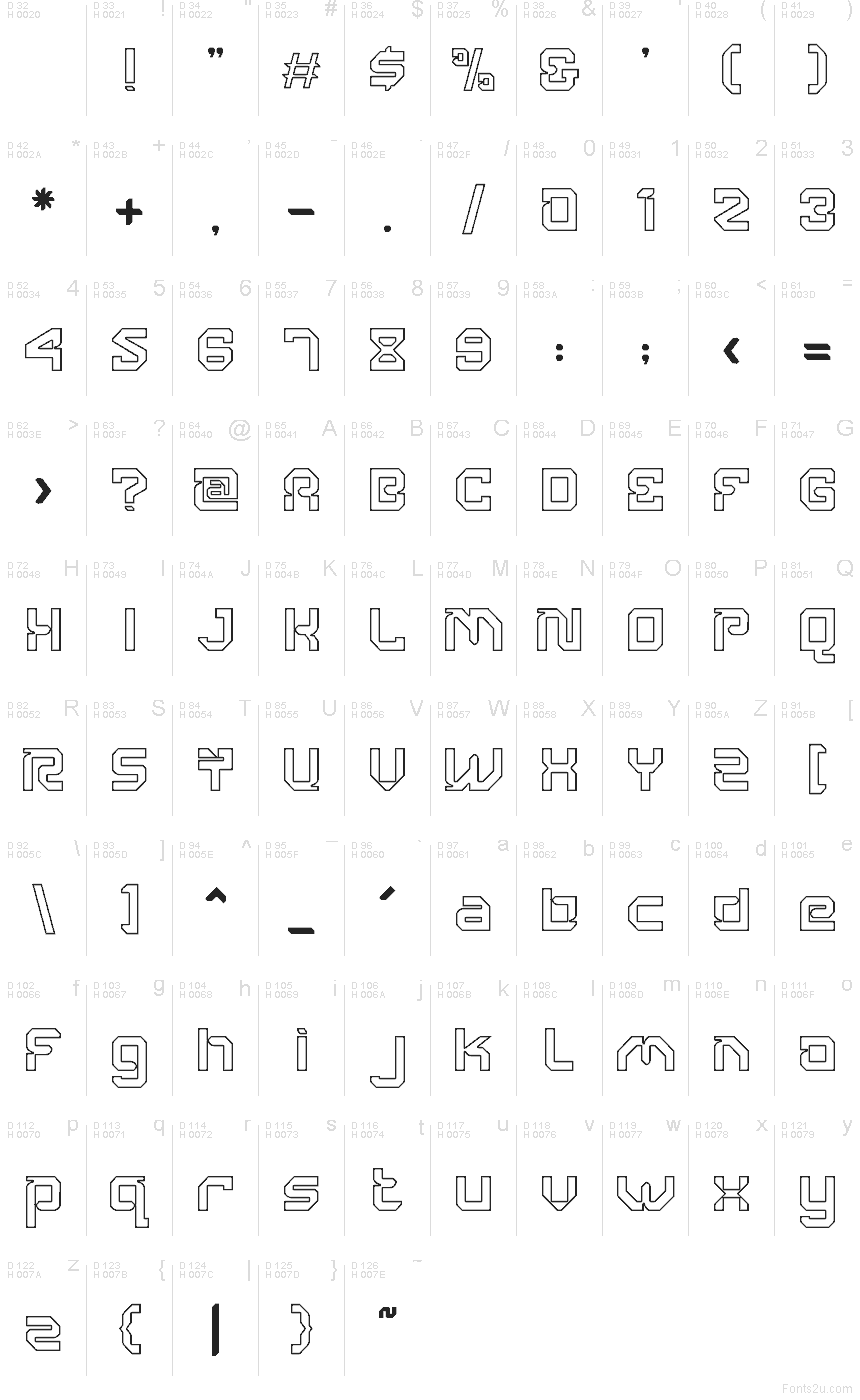
Cyber Crown Four od Putracetol Studio je bezplatné futuristické písmo typu outline, definované protáhlými čtvercovými liniemi a seříznutými rohy, které písmenům dodávají rytmus připomínající obvody. Konstrukce s dvojitou linkou udržuje tvary otevřené a lehké, takže design působí spíše jako obrysové panely nebo neonové trubice než jako masivní technický blok.
Tato struktura dává smysl u herních titulů, plakátů sci-fi, e-sportovního brandingu, hudebních letáků a nadpisů rozhraní, kde výrazná silueta odvádí hlavní vizuální práci. Otevřený obrys také poskytuje prostor pro vrstvení, což jej činí obzvláště užitečným pro koncepty log, úvodní obrazovky a grafiku na merchandising, které vyžadují ostrý digitální rám, aniž by působily příliš hustě.